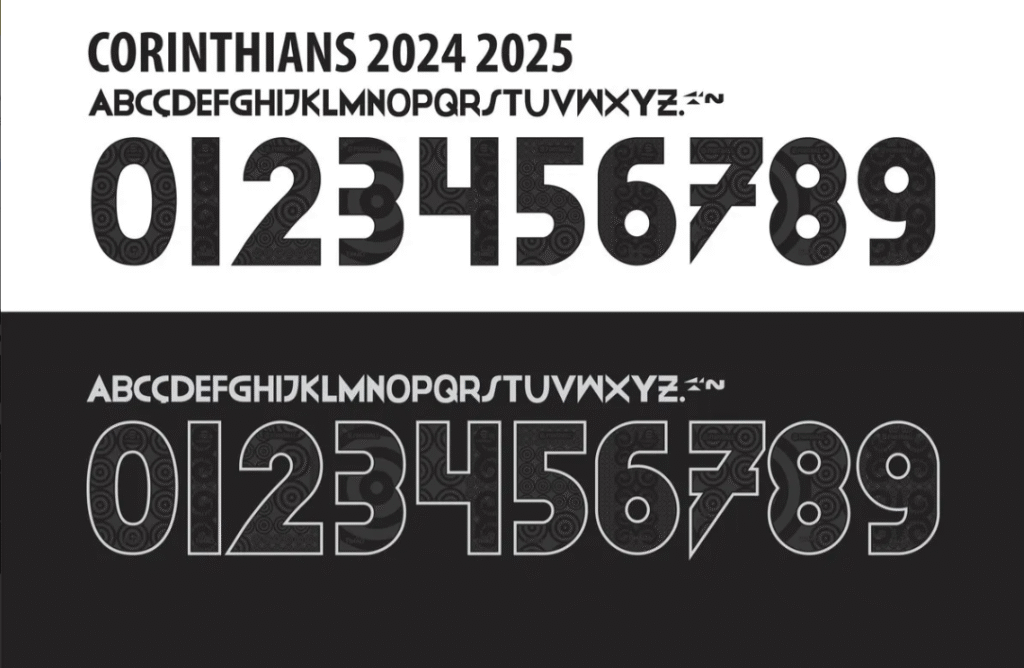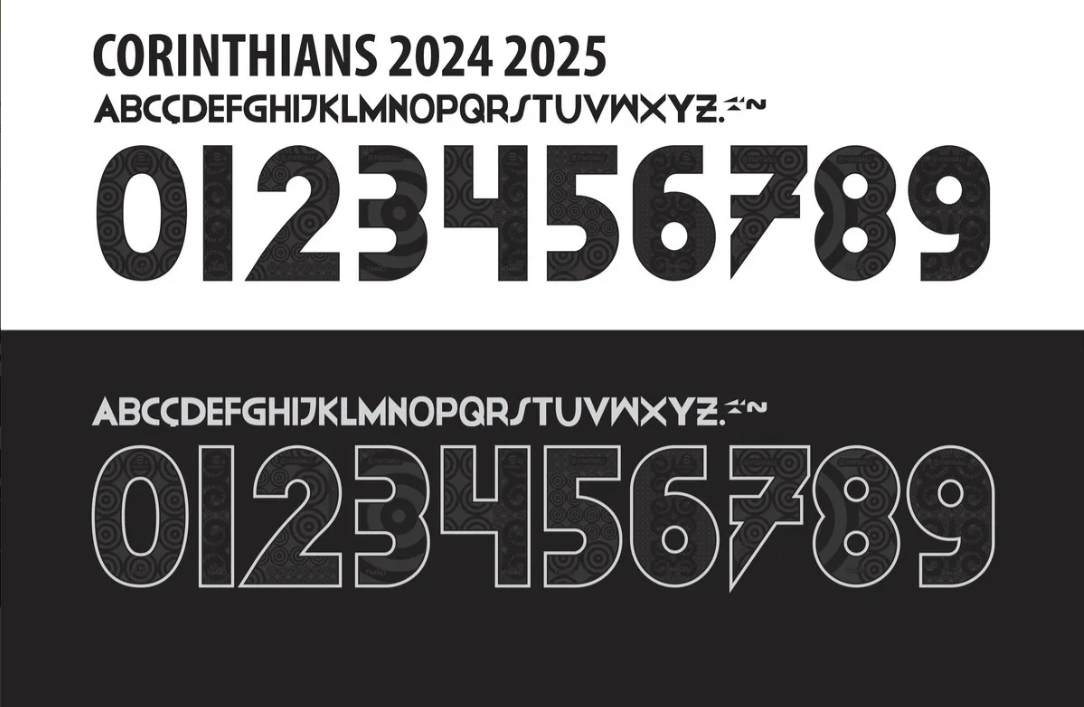
Para a temporada 2024-2025, a parceria entre o Timão e a Nike trouxe uma tipografia que reflete a modernidade e a atitude combativa do clube. Esta fonte é a peça-chave para quem deseja criar réplicas fiéis, estamparia de qualidade ou artes digitais com a cara do “Time do Povo”.
Estilo Visual e Identidade
A tipografia desenvolvida pela Nike para o Corinthians nesta temporada aposta em linhas sólidas e uma geometria robusta. Diferente de temporadas passadas que flertaram com estilos mais “grunge” ou texturizados (como na homenagem a Ayrton Senna), a fonte 2024-2025 preza pela legibilidade e impacto visual imediato.
Ela foi desenhada para brilhar tanto na camisa titular (branca) quanto no uniforme “all black” ou listrado. Os números possuem cortes estratégicos que dão uma sensação de velocidade e dinamismo, características típicas das criações recentes da Nike para seus clubes de elite global. É a escolha perfeita para estampar nomes de ídolos atuais ou personalizar o manto com o seu próprio nome.